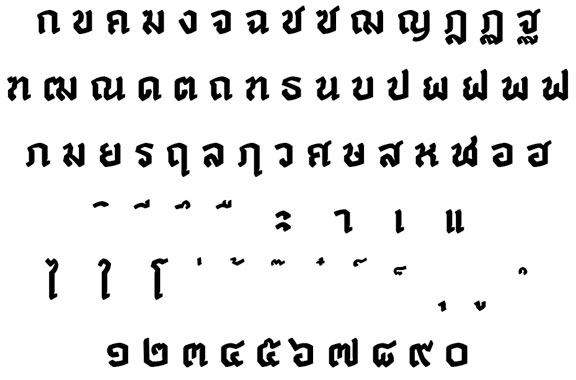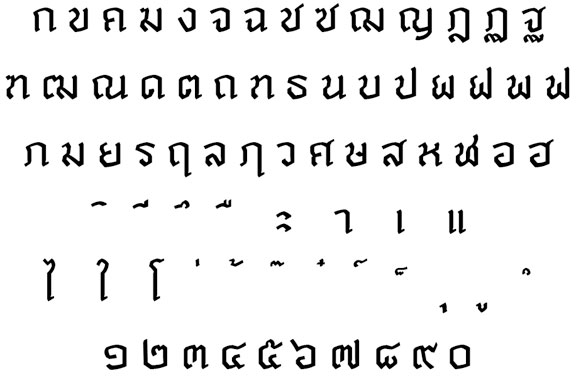
ต่อมาก็เป็นปัญหาเล็กๆน้อยๆครับ เป็นเรื่องการปรับรายละเอียดมากกว่า
- ตัวอักษรดูเอียงเกินไป ดูเหมือนจะล้ม  ฮิ้ววว
ก็เลยขยับฐานมันเล็กน้อย เพื่อให้ดูสมดุลย์ขึ้น
แล้วก็ทำให้เสร็จทั้งชุดอีกรอบครับ ดูภาพรวมอีกครั้ง
เอาล่ะ เริ่มเป็นรูปเป็นร่างแล้ว  ฮือๆ~
* สังเกตว่าผมจะเน้นคำว่า ภาพรวม บ่อยหน่อย เนื่องจากตัวอักษรเป็นสิ่งที่ทำงานเมื่ออยู่รวมเป็นชุดครับ
โครงสร้างที่เรากำหนดไว้ มันอาจจะใช้ไม่ได้กับตัวอักษรในทุกๆตัว ดังนั้นต้องผ่อนปรน และเปลี่ยนแปลงไปตามแต่ความเหมาะสม
การทำฟอนต์ดีๆ ซักตัวมีกระบวนการคิดและปรับเยอะเนอะ
ในตอนแรกผมก็คิดในใจ + ทำใจแล้วล่ะครับ ว่ามันน่าจะจบที่ตัวนี้แล้ว
แต่ภายในจิตใจมันก็ยังไม่ถูกใจครับ เพราะว่ามัน...(อธิบายไม่ถูก)
มันยังไม่พอใจ ผมเลยพยายามหาทางออกต่อไป
ผมเลยลองวาดเรื่อยเปื่อยครับ จนมาเจอกับรูปแบบสุดท้าย !
ผมตัดสินใจหักเส้นทุกเส้นที่เคยโค้ง เพิ่มความตรงเข้าไป
แล้วก็ได้เป็นแบบนี้ออกมา ตอนนั้นเลยคิดในใจว่า เฮ้ย! แบบนี้แหละ แบบนี้เลย
ผมจึงนำแบบร่างอันสุดท้ายนี้ ไปผสมกับตัวไฟนอล (ทางด้านบน)
เพราะแบบร่างใหม่มันค่อนข้างจะบางอยู่สักหน่อย จึงจับกฎข้อเดิมกลับมาใช้
1. เส้น หนา-บาง
2. รูปลักษณ์ของอักษรไทยนิเทศ
ตัววรรณยุกต์เองก็ปรับเช่นกันครับ
ของเดิม จะเห็นได้ว่ามันดูใช้งานยากเอามากๆ เพราะว่ามันดูมีลูกเล่นเยอะสุดๆ
ซึ่งจริงๆแล้วผมรู้สึกชอบวรรณยุกต์แบบนี้มาก แต่ต้องปรับเพราะว่าต้องทำให้เข้าชุดกับพยัญชนะ
และบางครั้งลูกเล่นแบบนี้มันอาจจะมากเกินไปเวลามาอยู่รวมเป็นประโยคมากๆ
ของใหม่
ตอนเห็น Process แบบอักษรนี้ทีแรกก็ลุ้นอยู่ว่า
ในโจทย์ "Siam Black Letter" แบบเดียวกะที่กรมพระยานริศฯ ดีไซน์ในยุคนั้นเนี่ย
ดีไซเนอร์ยุคเราจะตีแตกออกมาแค่ไหน แล้วในที่สุดก็ทำออกมาได้หลุดกรอบนั้นได้แค่ไหน
แล้วก็ออกมาเป็นอย่างที่เห็นนี่แหละครับ เจ๋ง
ดูสไตล์แล้วนึกถึงนิตยสารสารคดีเล่มล่าสุด ที่ปกเป็นหลวงปู่มั่น
แบบตัวอักษรหลักที่เป็นตีมของฉบับนี้ก็ได้อารมณ์คล้ายกัน แต่ไม่เหมือนกันครับ
และแล้วก็ครบชุดจนได้ครับ  ฮิ้ววว
ลองเป็นประโยคยาวๆดู
และเพื่อความสมบูรณ์ของชุดตัวอักษรมากขึ้น ผมจึงทำ bold ขึ้นมาเพิ่มเติม
ตัว bold เองก็ต้องมีการแก้ไขรายละเอียดเล็กๆน้อยๆเช่นกัน
- เพิ่ม inktrap เพื่อช่วยในเรื่องการลวงตา และทำให้ตัวอักษรดูไม่แน่่นจนเกินไป
- เส้นบางเส้นก็ต้องปรับเพื่อความเหมาะสม
- รายละเอียดที่มากเกินไป ต้องตัดออก
ลองเรียงกันหน่อย
ตัว bold นั้น จำเป็นจะต้องมีความแตกต่างกับตัว regular มากพอที่จะเห็นความแตกต่างที่ได้อย่างชัดเวลาใช้งานร่วมกัน
เสร็จสมบูรณ์แล้วจ้า  อ๊าง~
ลอง typesetting ซะหน่อย
พัฒนาการของตัวอักษรโดยสังเขป
ลองจัดในงาน layout ดู
ฮือๆ~ bold เนี่ยงามจับจิต
งามจับจิต ทั้ง bold ทั้ง regular  กรี๊ดดดดด กรี๊ดดดดด